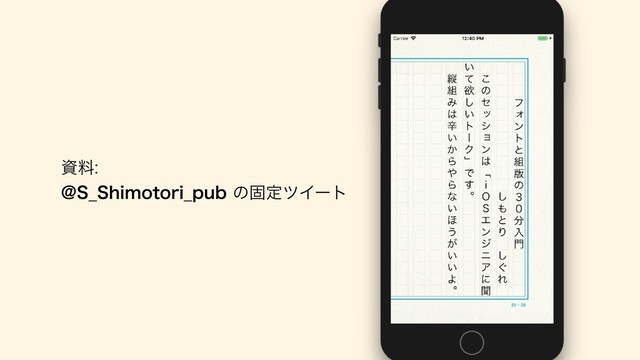
Introduction to Font and Typesetting
Shigure Shimotori
Introduction to Font and Typesetting
フォントと組版の30分入門
Shigure Shimotori
iOSΤϯδχΞʹ ฉ͍ͯཉ͍͠τʔΫ ʢ30ʣ
ϚδͰΨνͳτʔΫͰ͢ʂ
໘ന͍͔Βฉ͍ͯ΄͍͠τϐοΫ • ϑΥϯτͱ൛ͱ • ͍Ζ͍Ζͳݴޠͱ൛ • ҹΛ࡞Δ
ϑΥϯτͱ൛ͱ
׆൛ҹͷ༻ޠͰ͢ʂ
׆൛ҹͷͳ͕Ε ׆ࣈΛ Έ൛ʹͯ͠ Δʂ ҹതؗʹͯɻ
ϑΥϯτ ίϯϐϡʔλʔͰ͏จࣈͷσβΠϯͷ͜ͱɻ׆ࣈͷ࣌ ʹɺಉ͡ॻମͰಉ͡αΠζͷ׆ࣈηοτΛࢦ͢ݴ༿Ͱ ͕͋ͬͨɺిࢉࣸ২DTPͰͻͱͭͷϑΥϯτͰ֦େ ॖখɺมܗ͕Ͱ͖ΔͨΊɺଠࣈࣼମͳͲͷελΠϧΛؚ ΊͯϑΥϯτͱݺͿΑ͏ʹͳͬͨɻ ASCII σδλϧ༻ޠࣙయΑΓ
൛ ݪߘʹج͍ͮͯ׆ࣈΛΈɼ࠷ऴతʹ൛Λ࡞Δ·Ͱͷ ࡞ۀ͓Αͼͨ͠൛ɽ ʢதུʣ खಈɼػց͞ΒʹίϯϐϡʔλͰ͋ͬͯɼ൛ͱ͍͏ දݱΘΕ͍ͯΔɽ ਤॻؗใֶ༻ޠࣙయ ୈ4൛ΑΓ
ݱࡏʢ1985ʙʣ
׆൛ҹͷ͓͜͜·Ͱʂ
͍Ζ͍Ζͳݴޠͱ൛
͜Μͳͱ͜Ζʹ൛͕ʂ • ӳޠͰ #શ෦ಉ͡͡Όͳ͍Ͱ͔͢ SPACEฤ • ຊޠͰiOSॎॻ͖ʹઓ • λΠޠͰTall Script
• ΞϥϏΞޠͰRTLͱ߹ࣈ
ӳޠͰ #શ෦ಉ͡͡Όͳ͍Ͱ͔͢ SPACEฤ
ͬͱΑ͘ݟΖʂ
͓ l*OUSPEVDUJPOUP'POUBOE5ZQFTFUUJOHz
ҹΛ࡞Δ͓ • PDFͱϑΥϯτͷ͓ • ϦονͳΦϓγϣϯ
PDFͱϑΥϯτͷ͓
࠶ܝɿAppleͱAdobeͷਤ AldusAdobe͕ඒຯ͘͠৯·ͨ͠
PDF͕อ࣋͢Δใʢྫʣ • ༻ࢴαΠζ • ϑΥϯτใ • ίϯςϯπΛஔ͢ΔҐஔ • ςΩετ •
ਤܗ
ϑΥϯτσʔλͲ͜ʁ Ӿཡऀͷίϯϐϡʔλʹ͓·͔ͤ or ඞཁͳͿΜΛPDFࣗͰอ࣋ or ΞτϥΠϯԽͯ͠ϑΥϯτใഁغ ຒΊࠐΈʁ Apple
Chancery →
ϦονͳΦϓγϣϯ
ͩ͜ΘΓϙΠϯτ͜͜ʂ ☑ ࢴ͕ްΊ ☑ ಛघࢴΛ͍ͬͯΔ ☑ ༡ͼࢴΛೖΕ͍ͯΔ ☑ ഩΛೖΕ͍ͯΔ ☑
৭͕ଟ͍ ☑ ಛ৭Λ͍ͬͯΔ ໊ʹ͓ۚΛ͏ͷָͦ͠͏
·ͱΊ • ׆൛ҹͷӨڹະͩڧ͠ • ֤ݴޠͷಛͷѲ͕େࣄ • ॎॻ͖қ͕ߴ͍ • ࣮ߦҕһޫΓ͕͖ͬͯ͝ຊਓ͕͓ͬ͠Όͬͯ·ͨ͠